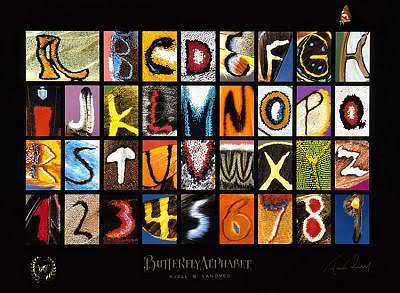
Wie hübsch, was einem so alles vor die Maus kommt, wenn man was ganz anderes sucht:
Ein Alphabet aus Schmetterlingsaugen, leider noch ohne Versal-ß und ohne Ligaturen :-)
Das mit den Schmetterlingsaugen ist ja absolut genial.
Unglaublich, wie schön die Ziffern sind :D ... und so klar!
Das angucken und dann evtl. eine Idee für neue Lernplakate bekommen?
nicht nur das, ich will auch im Sumpf stehen und Libellen fotografieren. :-)